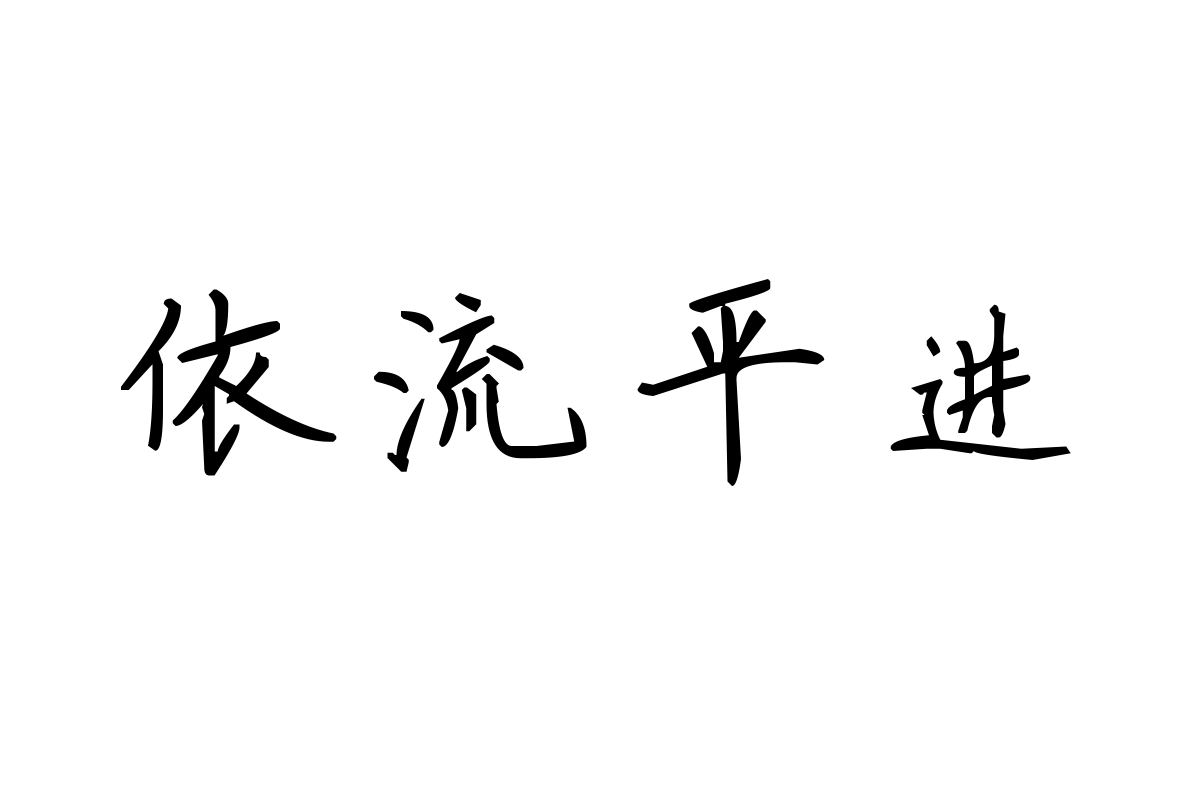
米开同桌的你字体是一款具有独特设计感的中文字体,由著名设计师米开创作。这款字体采用了简洁而优雅的设计,线条流畅,结构紧凑,给人一种清新、自然的感觉。在字形上,米开同桌的你字体保留了传统的汉字书写特点,同时融入了一些现代设计元素,使其更加符合现代人的审美需求。
该字体适用于各种场景,如书籍、杂志、海报、网页等。无论是用于正式的商务文档还是轻松的日常交流,米开同桌的你字体都能展现出其独特的魅力。此外,这款字体还具有较高的可读性,适合用于需要清晰显示文字的场合。
总的来说,米开同桌的你字体是一款非常优秀的中文字体,无论是从设计感还是实用性方面都表现出色。如果你正在寻找一款能够提升你作品美感和品质的字体,那么不妨尝试一下米开同桌的你字体。